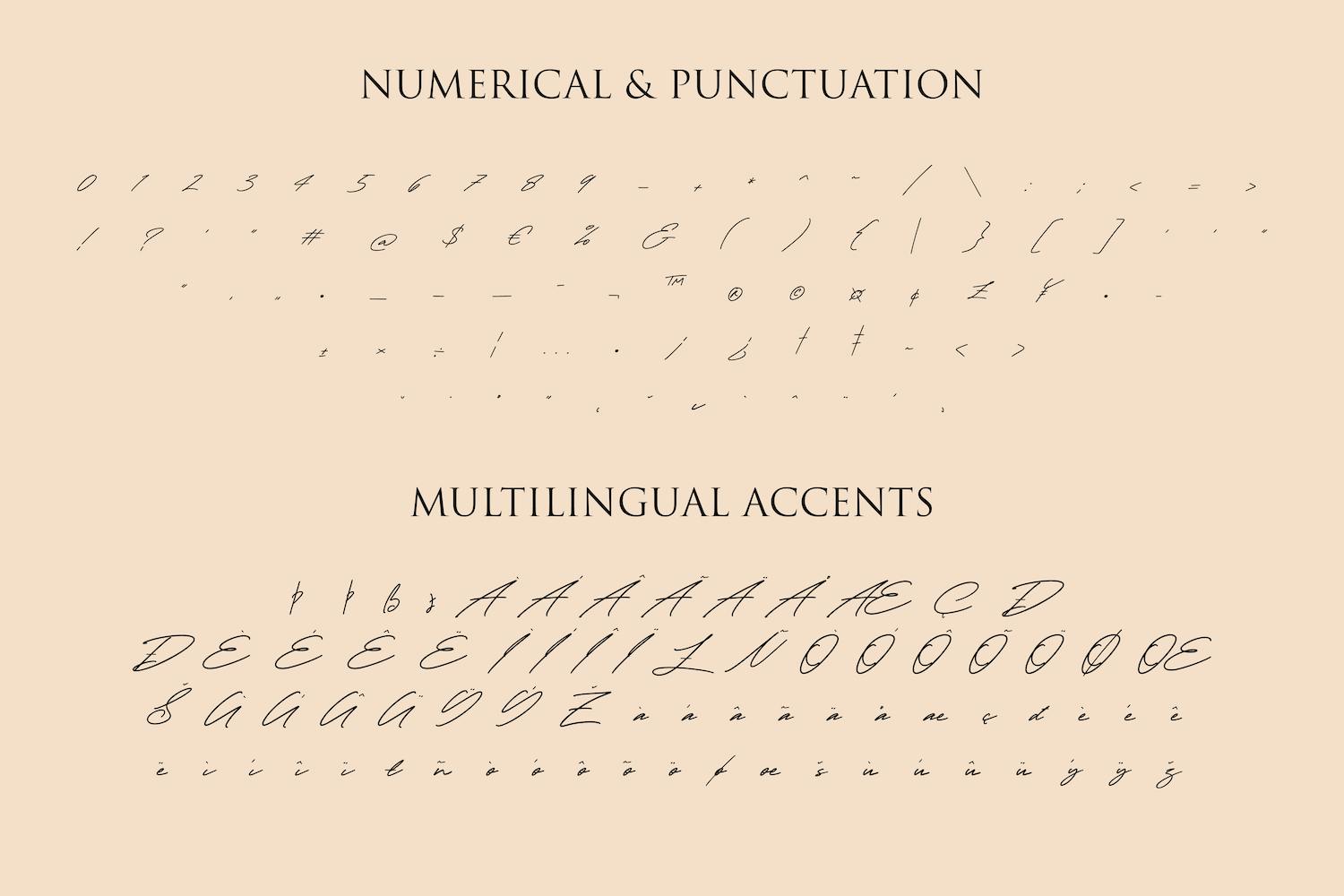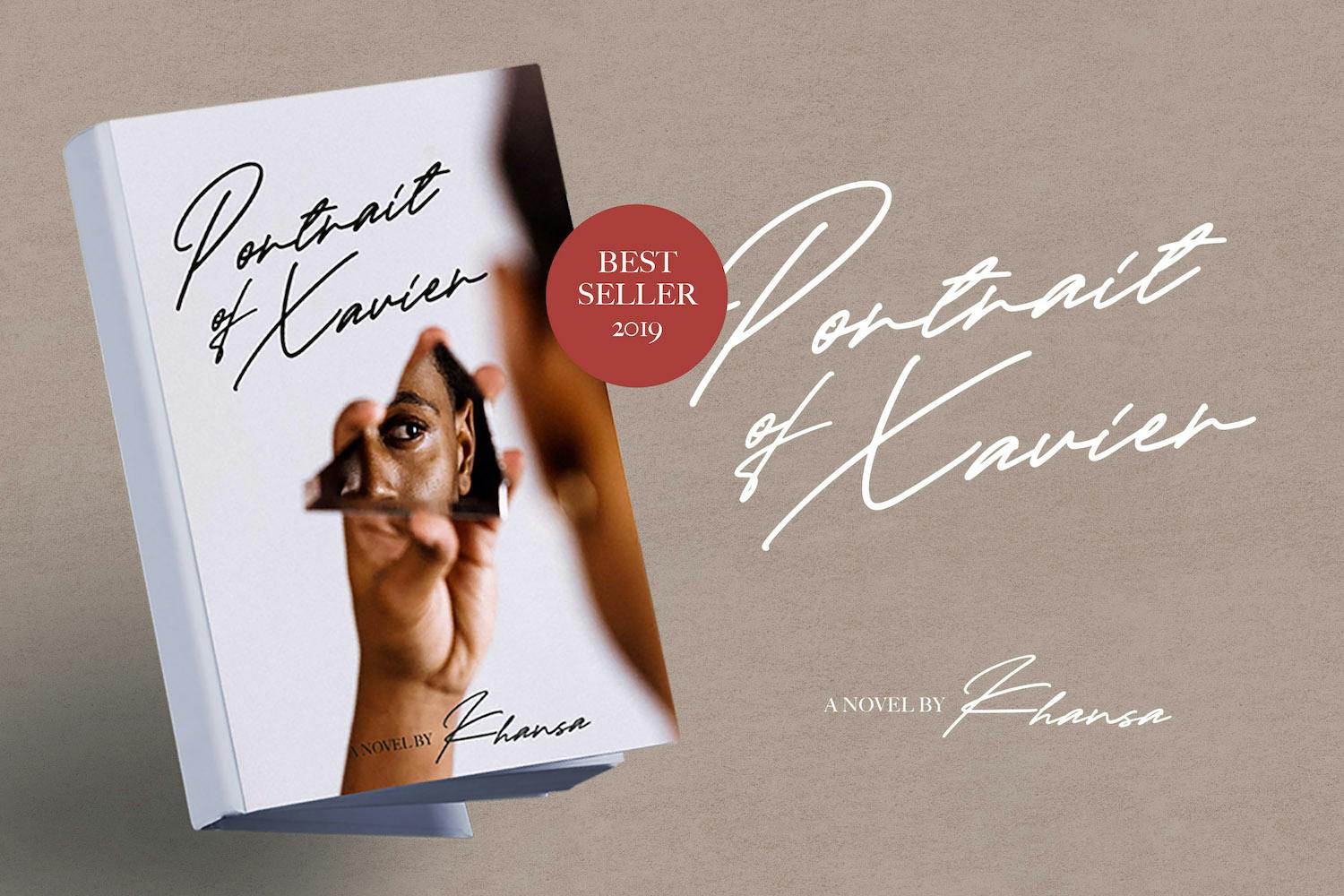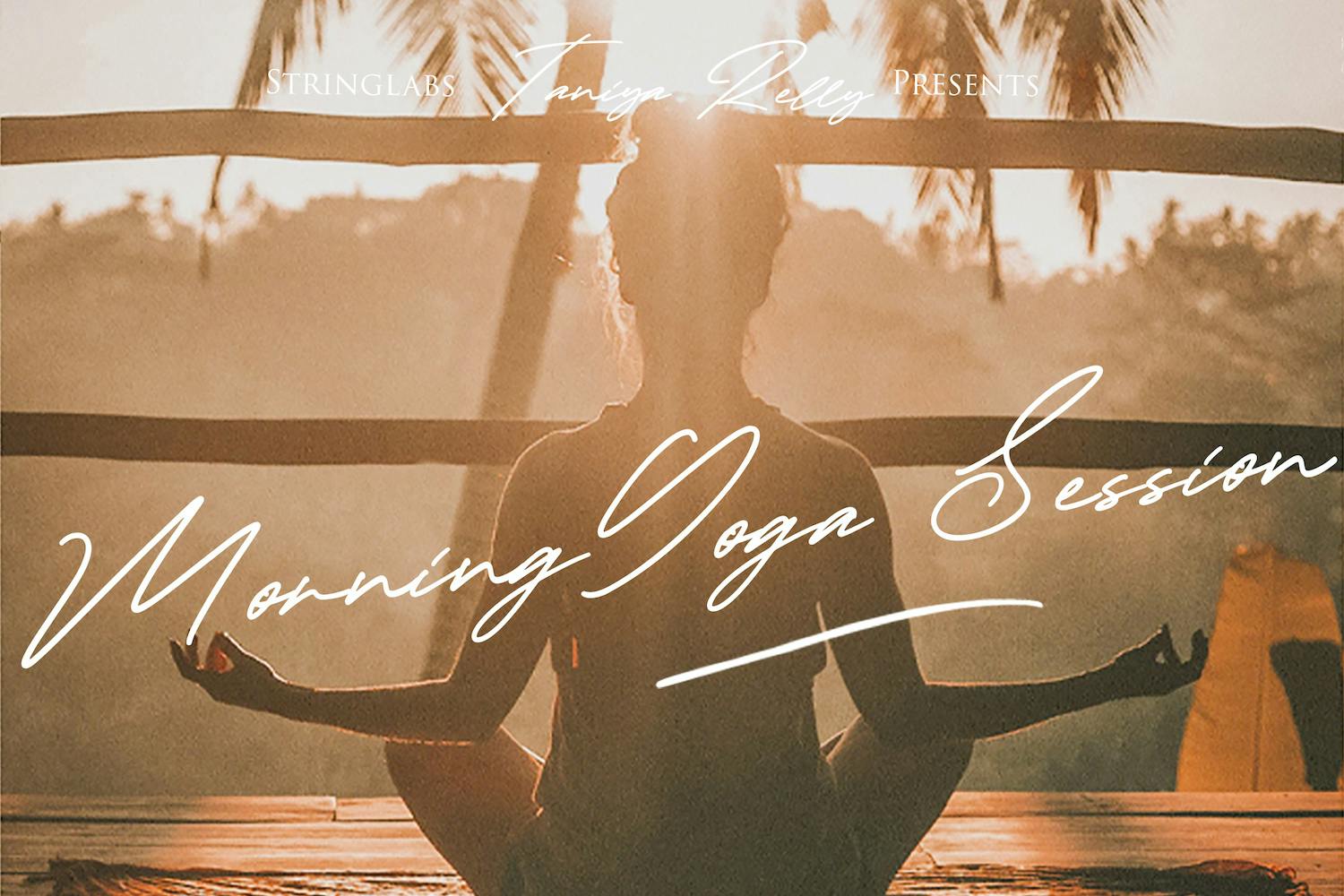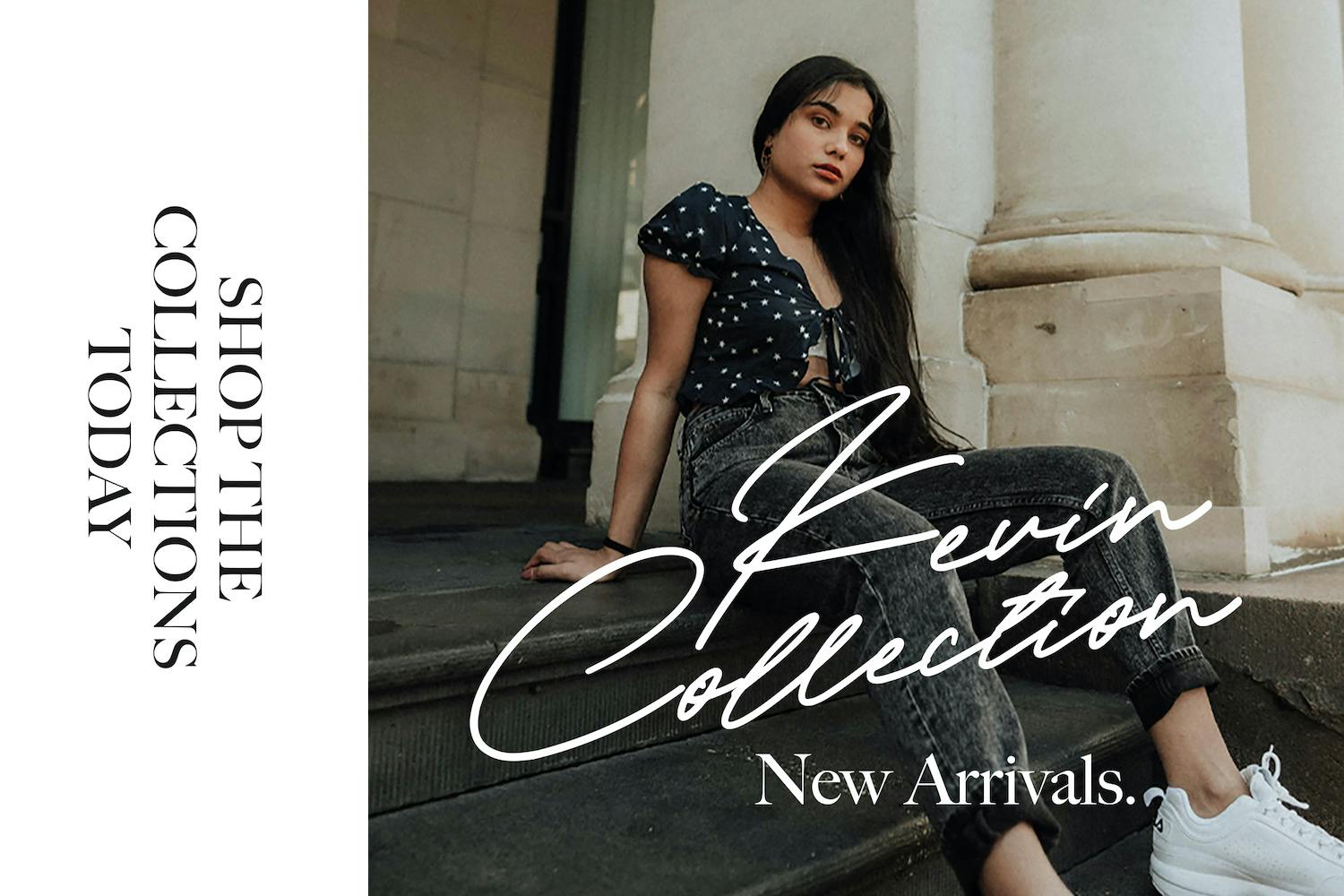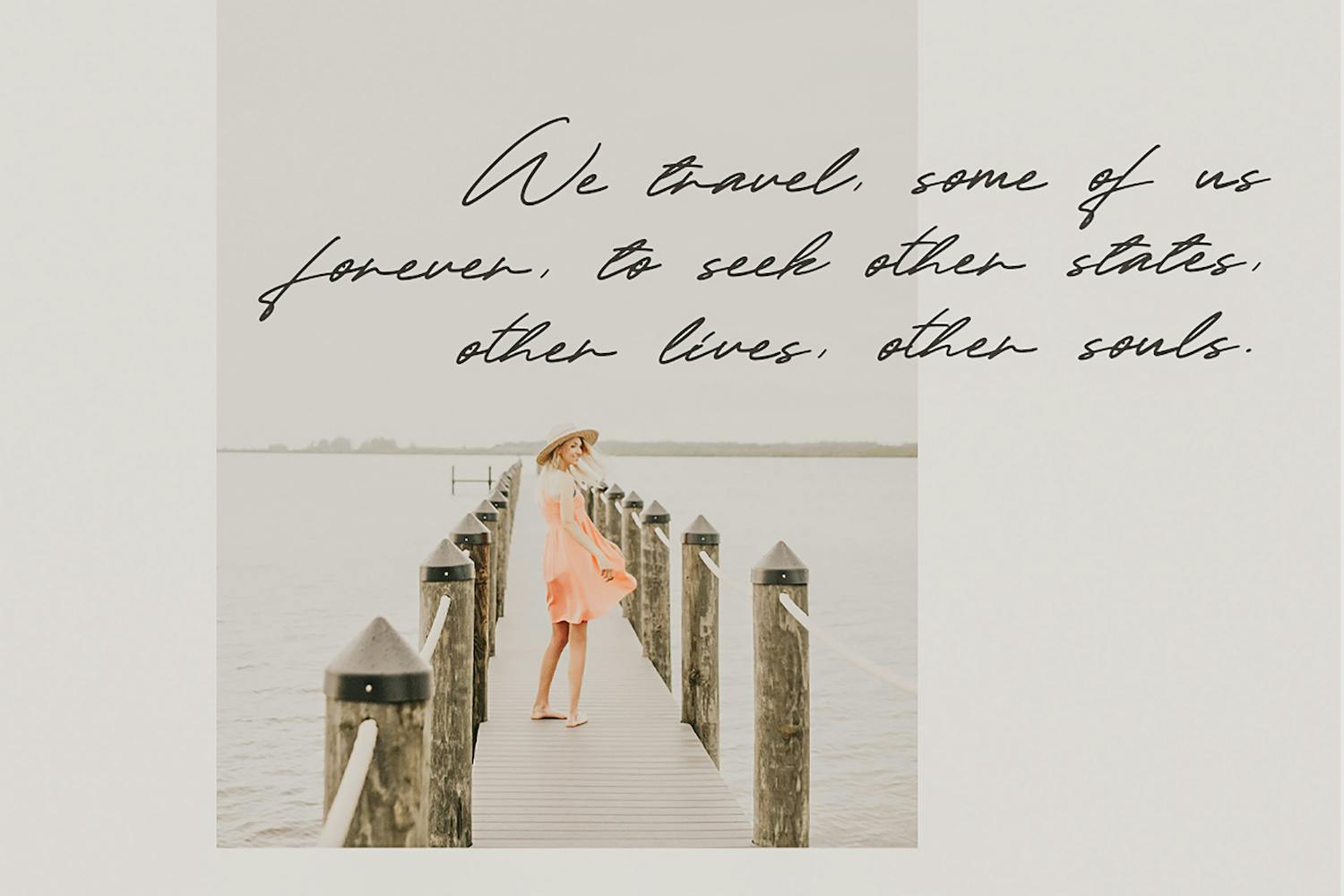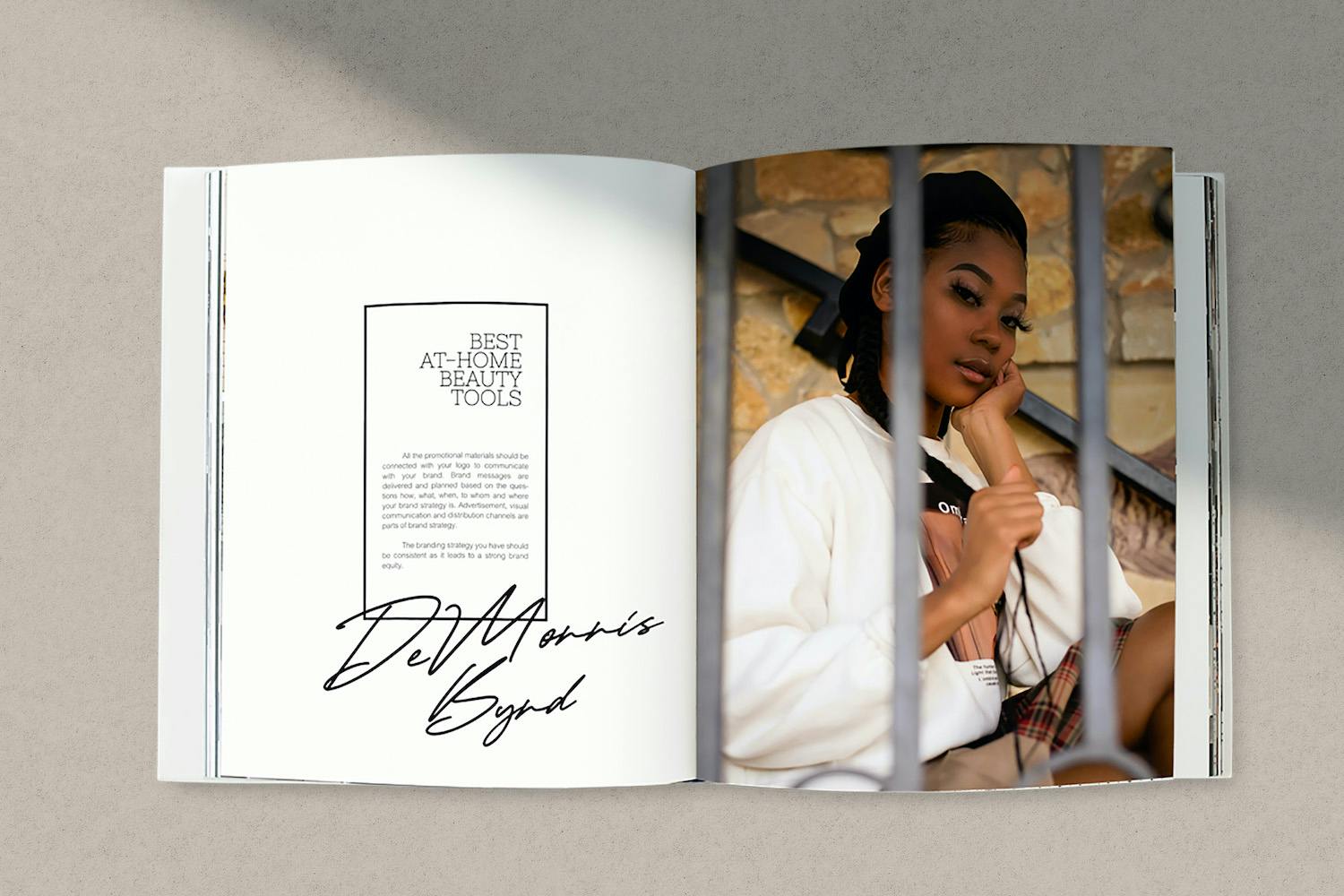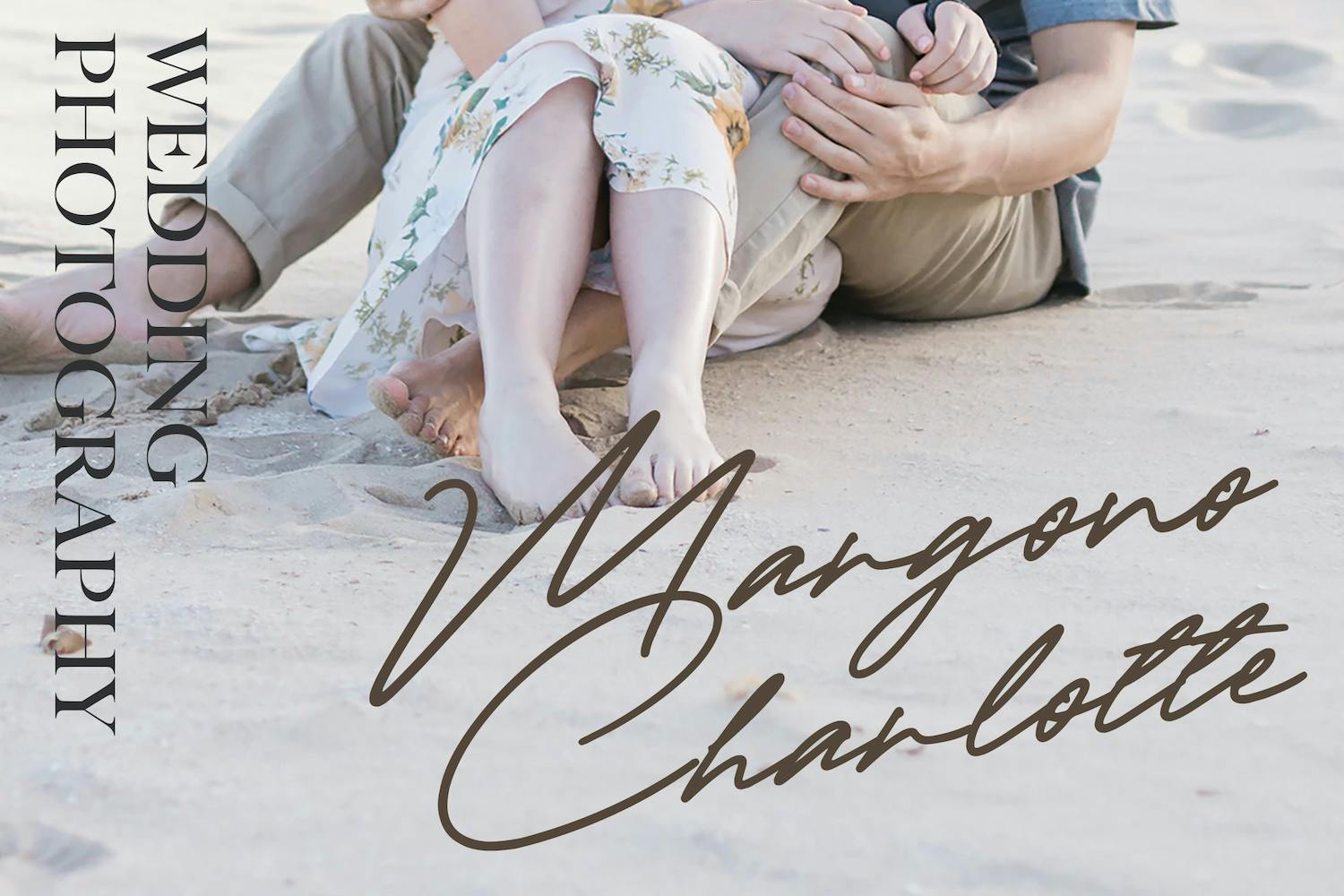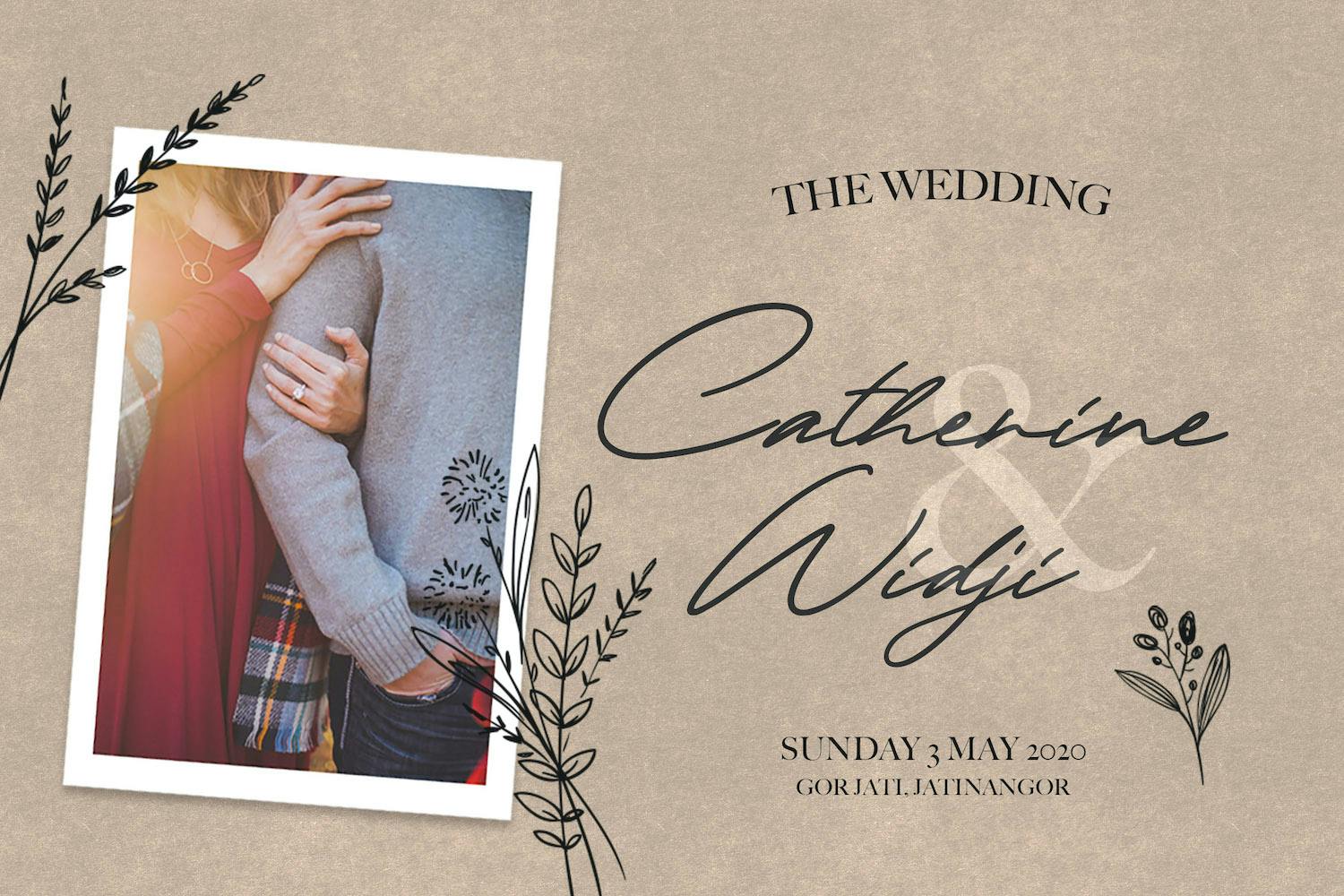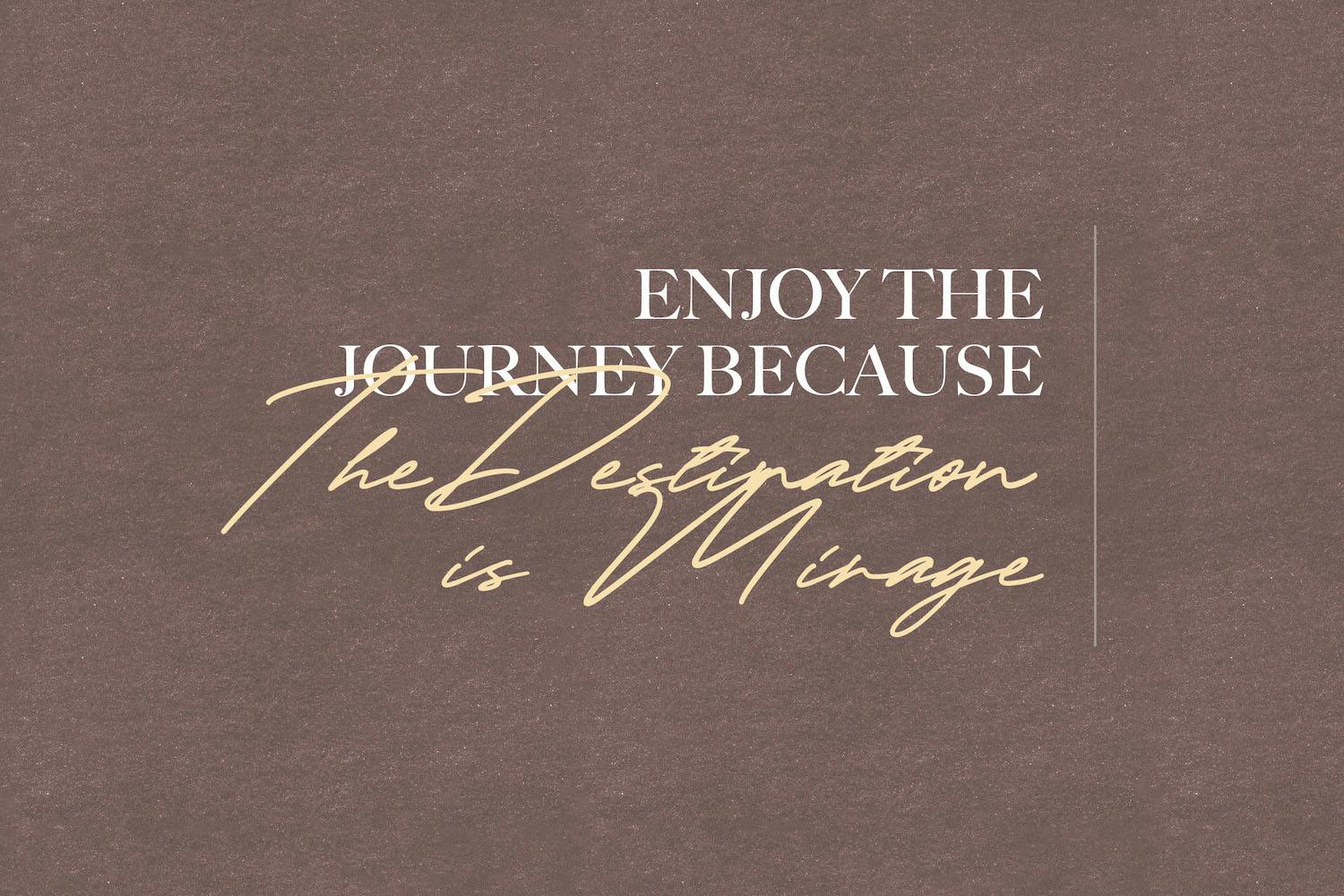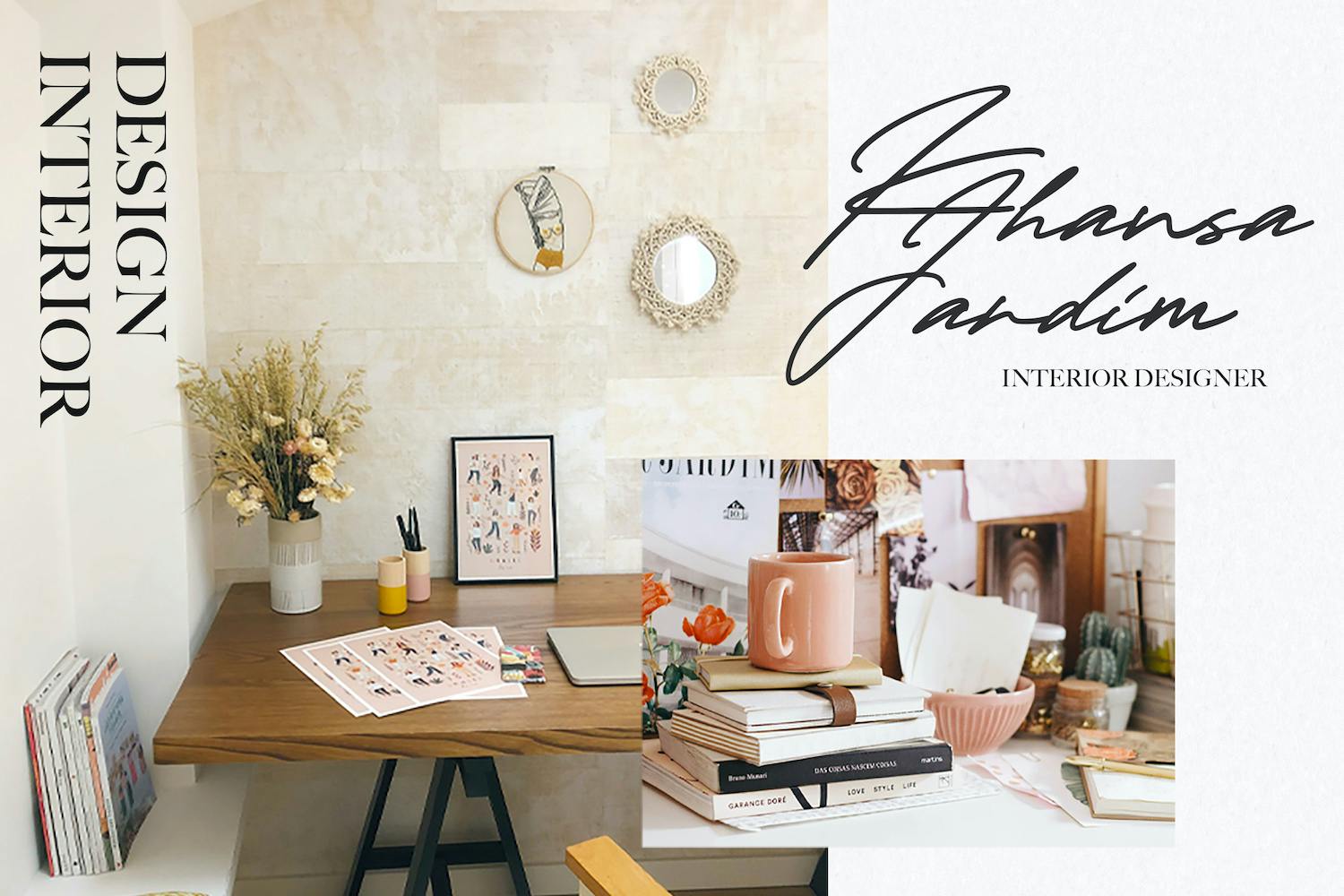
Taniya Relly Luxury Signature Font
فونت Taniya Relly با سبک امضای دست‌نویس، مناسب برای طراحی‌های خاص شما.
معرفی Taniya Relly - فونت امضای لوکس
فونت Taniya Relly یک فونت اسکریپت با سبک امضای دست‌نویس است. این فونت با استفاده از قلم موی دست‌نویس واقعی طراحی شده و برای برندهای مد، دعوتنامه‌های عروسی، کارت‌های ویزیت، لوگوها، امضاها و همچنین خوشنویسی بسیار مناسب است.
این فونت شامل مفاهیم شیک،Elegant، خلاقانه و منحصر به فرد است.
ویژگی‌ها
• لیگاتورها
• جایگزین‌ها
• حروف بزرگ و کوچک
• اعداد و نشانه‌گذاری‌ها
• پشتیبانی چند زبانه